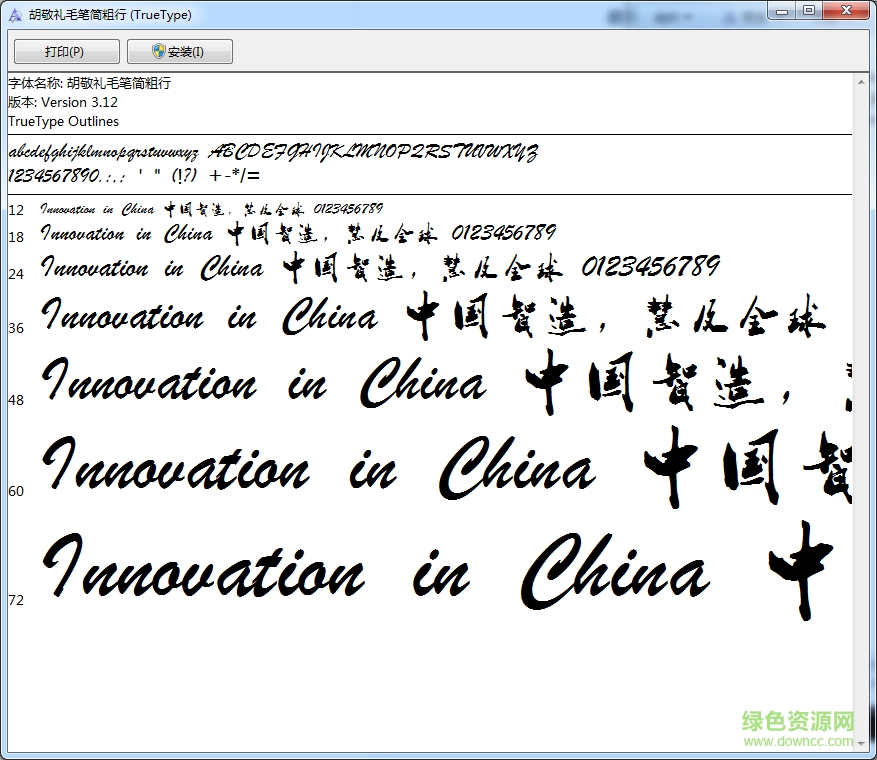
胡敬禮毛筆粗行字體是一款比較常用的電腦字體,字體粗細(xì)有致,線條感十足極具美感,適用于海報(bào)設(shè)計(jì)、圖文印刷、美工創(chuàng)作等多種領(lǐng)域,一鍵安裝便可使用。快來(lái)綠色資源網(wǎng)下載體驗(yàn)吧!
胡敬禮毛筆粗行字體是一款用于毛筆手寫設(shè)計(jì)方面的字體,整體字體筆畫運(yùn)筆飄忽快捷,筆跡粗壯,是一種風(fēng)格相當(dāng)獨(dú)特的字體。該字體適用于創(chuàng)意設(shè)計(jì)、藝術(shù)設(shè)計(jì)、書(shū)寫設(shè)計(jì)等方面,需要的話可以來(lái)下載使用。